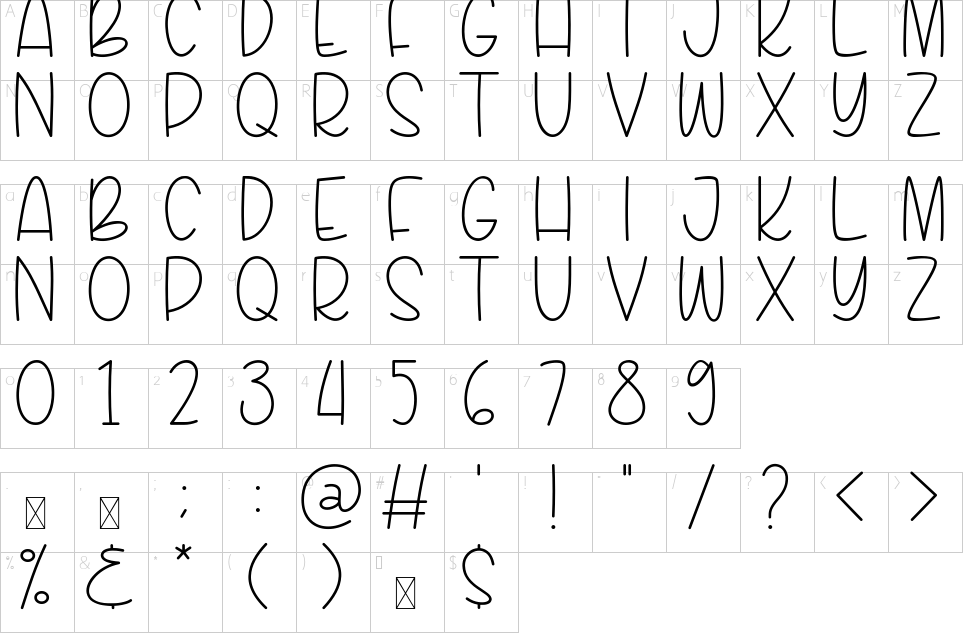
Aqui está uma descrição em português para a página de download da fonte ‘Microwave Font | 1001 Free Fonts’: Microwave Font é uma fonte grata e elegante disponível para Windows e Mac. Criada pela equipe da Jimtype Studio, esta fonte oferece um design minimalista que combina perfeitamente com diversos estilos de design. Seja você um designer gráfico ou um web designer, esta fonte pode complementar seus projetos de forma simples e eficaz. Com um design contemporâneo e agradável, a Microwave Font permite que você personalize seus textos de maneira única e criativa. Estamos felizes com cada download dessa fonte, e esperamos que ela faça uma grande diferença em seus projetos. Não deixe de experimentar essa fonte grátis e descubra por si mesmo o seu poder!